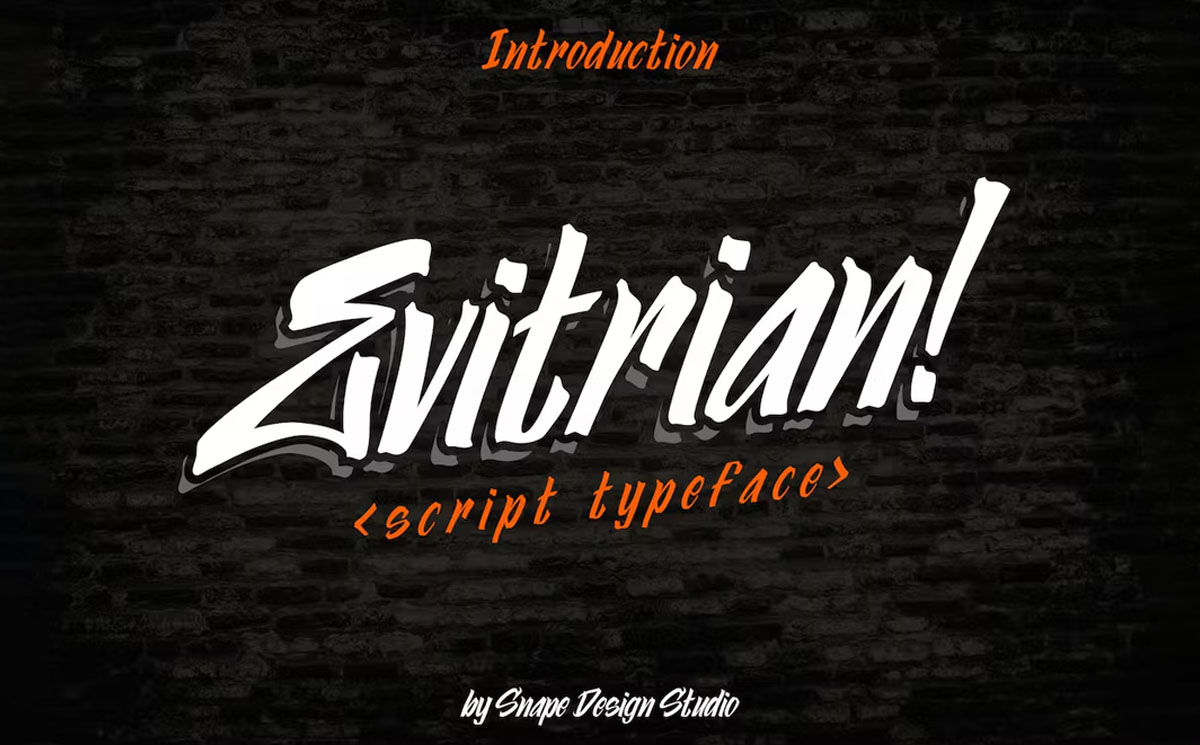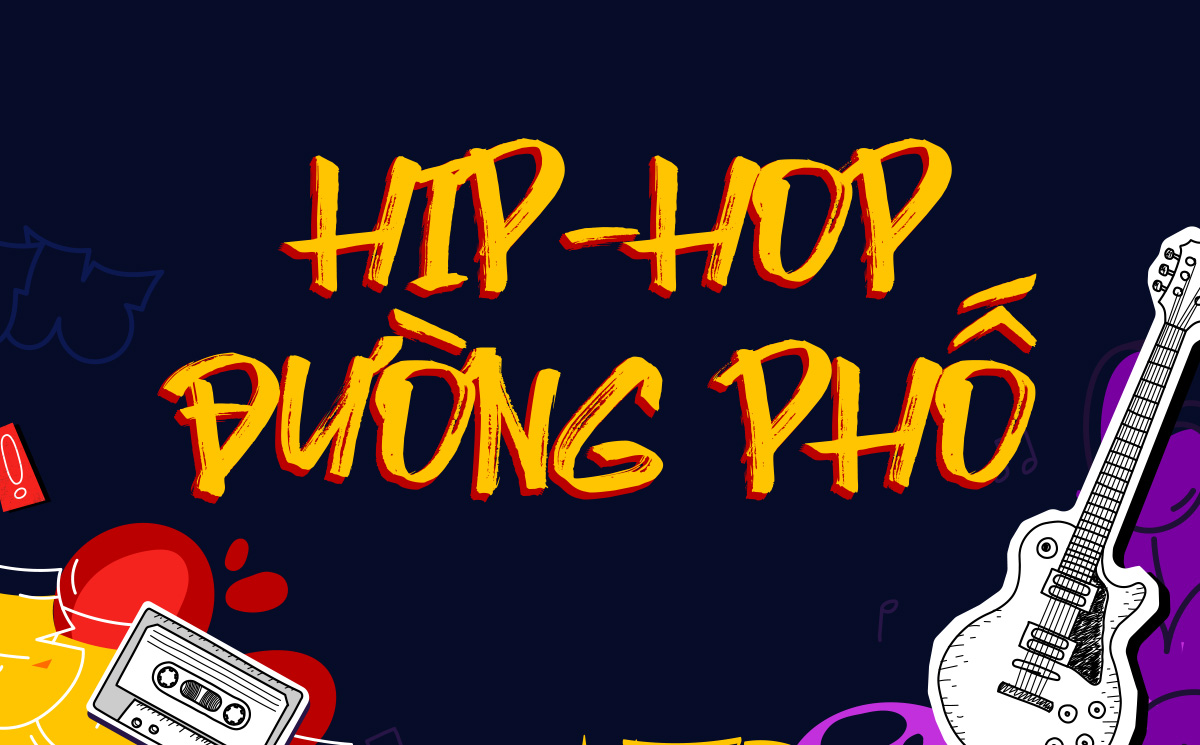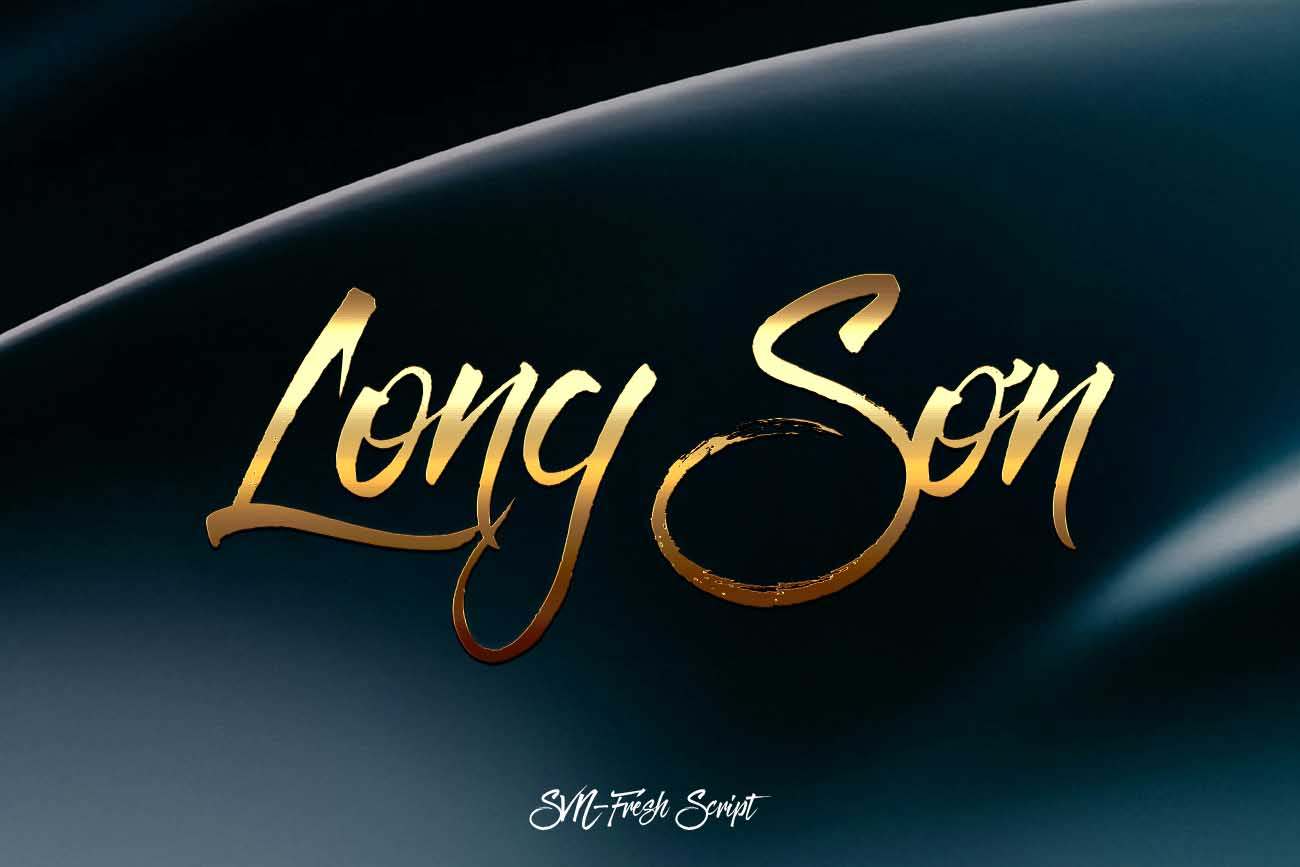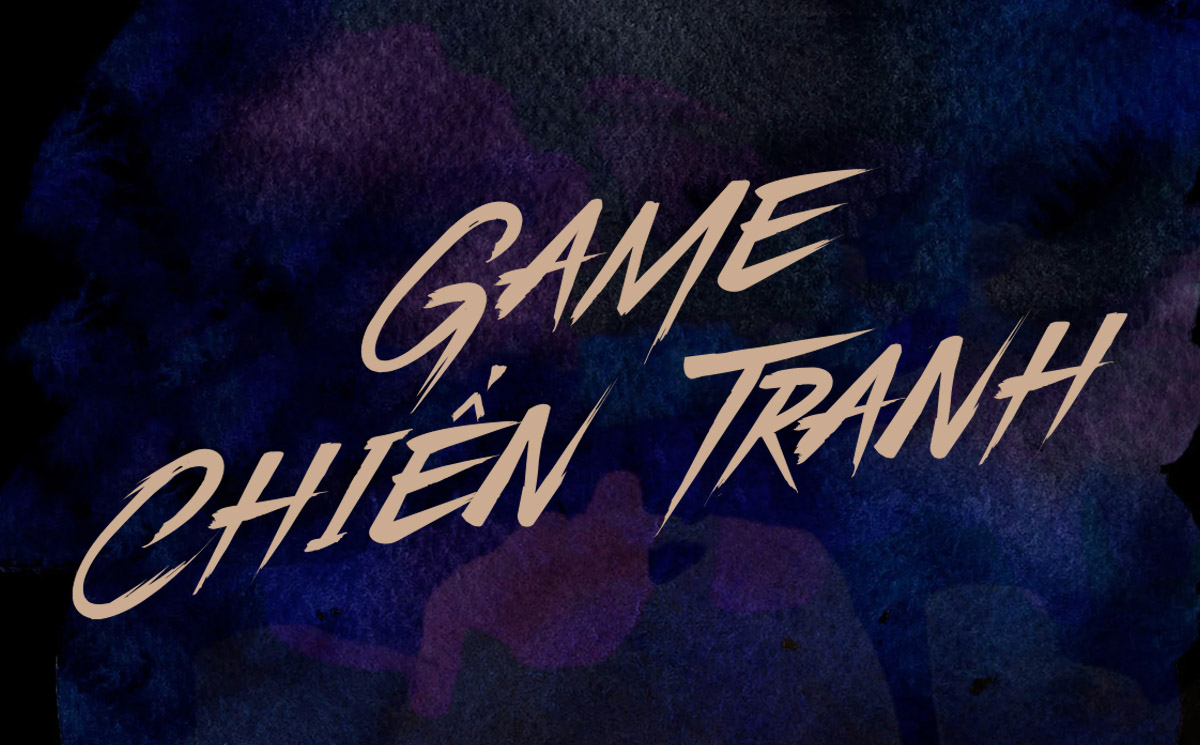
[Tải Xuống] Tổng Hợp Các Font Chữ Graffiti Việt Hóa Đẹp Cho 2026
Khám phá bộ sưu tập font chữ graffiti Việt hóa 2026 đẹp, cá tính, đầy chất đường phố, phù hợp poster, logo, áo thun và thiết kế hiphop.
Trong thiết kế hiện đại, font chữ graffiti đang dần trở thành lựa chọn yêu thích của nhiều nhà thiết kế trẻ bởi sự phóng khoáng, táo bạo và đầy chất nghệ thuật mà nó mang lại. Không chỉ dùng để truyền tải thông điệp, font còn giúp tạo dấu ấn riêng cho thương hiệu hoặc sản phẩm. Nếu bạn đang muốn làm mới thiết kế theo phong cách đường phố năng động, bài viết này chính là nơi để bắt đầu.
Tại Fontdep.vn, chúng tôi đã tuyển chọn những bộ font graffiti Việt hóa đẹp nhất năm 2025 – đa dạng kiểu dáng, dễ sử dụng và đặc biệt là hỗ trợ tiếng Việt đầy đủ. Bạn có thể dùng cho nhiều mục đích như thiết kế áo thun, poster, banner âm nhạc, bìa truyện tranh hoặc logo thương hiệu cá tính.
Font chữ graffiti là gì?
Font chữ graffiti là kiểu chữ lấy cảm hứng từ nghệ thuật vẽ tường đường phố – nơi chữ viết trở thành một phần của biểu đạt cá nhân và phong trào văn hóa. Những font này thường có đường nét to, đậm, được tạo hình một cách tự do, phá vỡ khuôn mẫu truyền thống. Có font nghiêng ngả, có font như chảy sơn hoặc được xịt lên bề mặt tường bằng bình sơn phun.
Phong cách này thường gắn liền với văn hóa hiphop, rap, underground, hoặc những thiết kế mang tinh thần nổi loạn, độc lập và tự do thể hiện bản thân.
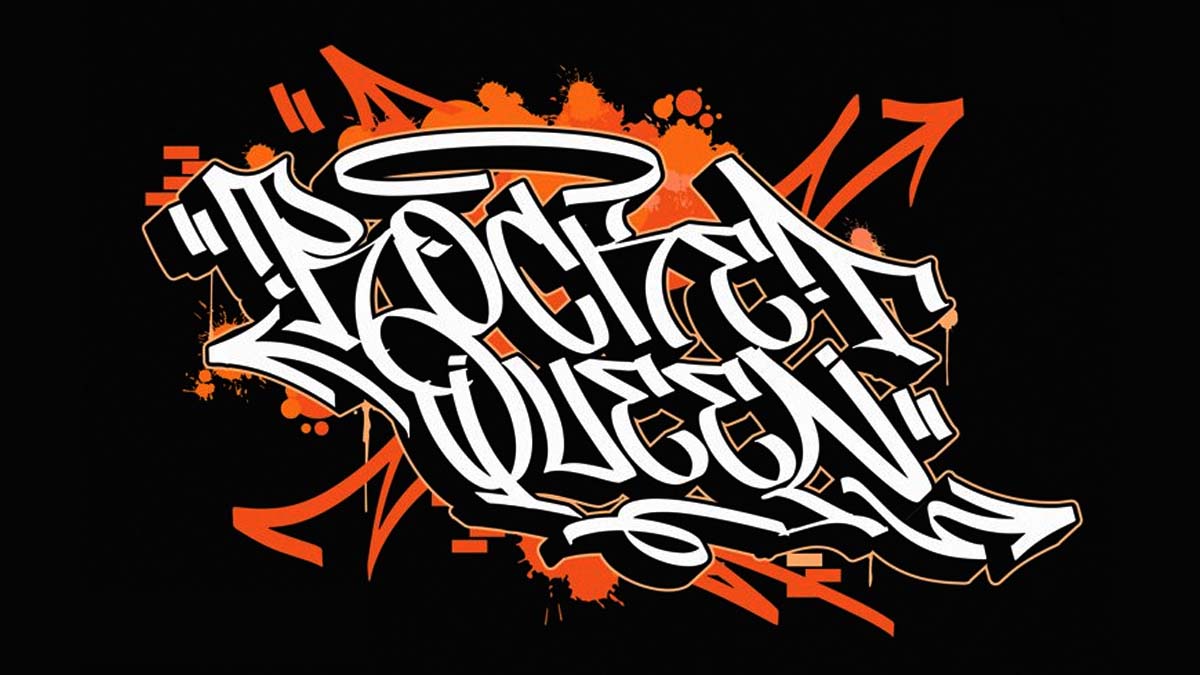
Những điểm nổi bật của font chữ graffiti
- Đường nét mạnh mẽ, không gò bó: Các ký tự được tạo hình đa dạng, không theo một cấu trúc cứng nhắc nào.
- Tính thẩm mỹ đậm chất nghệ thuật: Nét chữ có thể mang phong cách chảy sơn, 3D, bubble hoặc graffiti cổ điển.
- Dễ gây ấn tượng thị giác: Dùng làm tiêu đề, logo hoặc chữ nhấn rất hiệu quả.
- Hỗ trợ tiếng Việt: Nhiều bộ font đã được Việt hóa, có dấu đầy đủ – tiện dụng trong thiết kế nội địa.
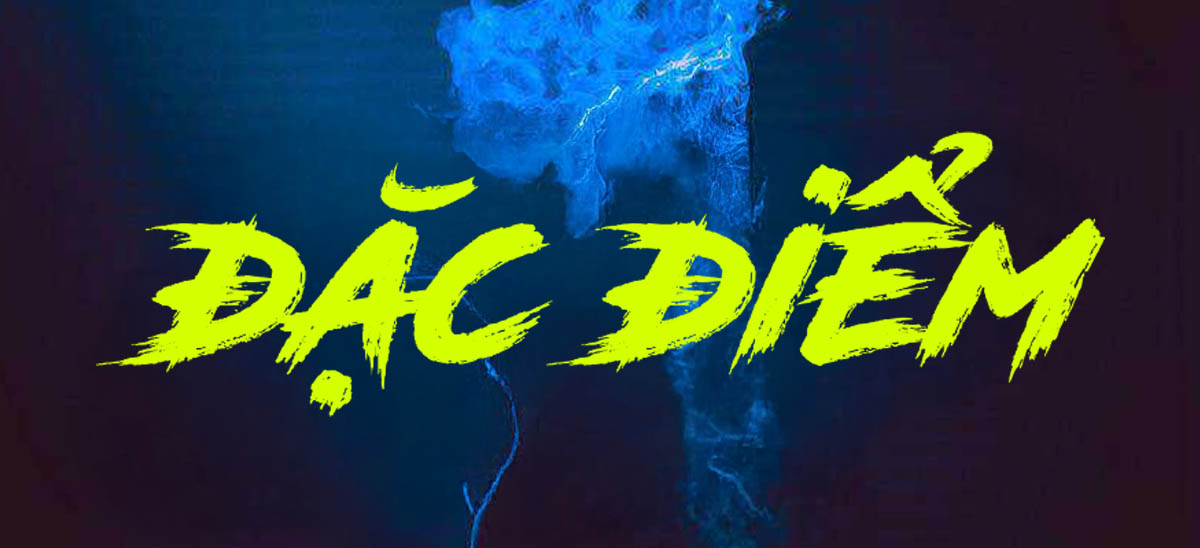
Top 13+ Font chữ graffiti Việt hóa đẹp nhất 2025
Dưới đây là một số font graffiti đã được Việt hóa đầy đủ, dễ sử dụng và cực kỳ ấn tượng trong thiết kế:
1. MJ Brostone – Bay Bổng & Tự Nhiên | Font chữ graffiti Việt hóa
MJ Brostone sở hữu kiểu chữ viết tay bằng cọ với đường nét mềm mại, hơi nghiêng về phải tạo cảm giác uyển chuyển, thoải mái. Các chữ cái có độ cao đồng đều, sắp xếp gọn gàng, giữ được sự ngẫu hứng nhưng vẫn dễ đọc. Phần đuôi chữ được kéo dài tinh tế giúp tổng thể font trở nên sinh động và mang hơi thở hiện đại, phù hợp với nhiều loại thiết kế mang tính cá nhân.
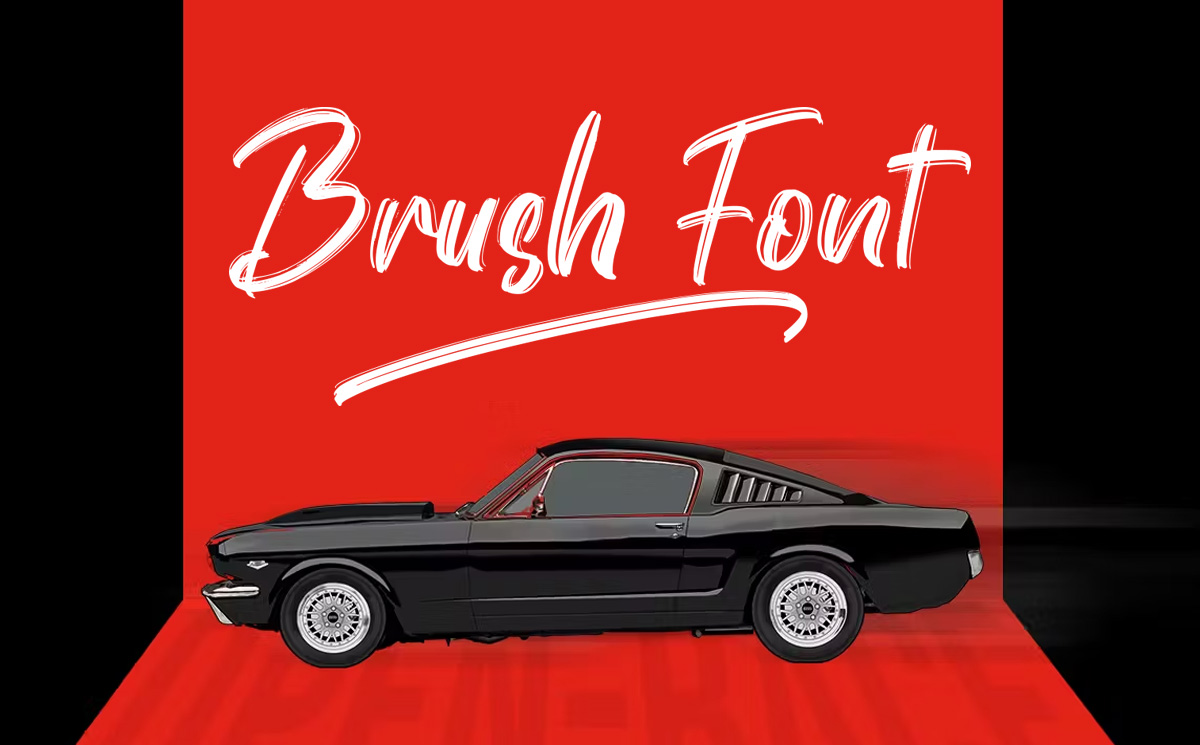
2. SVN Road Rage – Mạnh Mẽ & Bùng Nổ | Font chữ graffiti brush
SVN Road Rage mang đến cảm giác như được vẽ bằng cọ, với những nét chữ lớn, sắc cạnh và có phần rách gân ở đầu hoặc đuôi. Từng ký tự như được hất mạnh tay, tạo nên hiệu ứng chuyển động quyết liệt và đầy tính áp lực. Phông chữ này truyền tải sự khẩn trương, mạnh mẽ và năng lượng bùng nổ – rất thích hợp cho các thiết kế cần gây ấn tượng thị giác mạnh ngay từ cái nhìn đầu tiên.
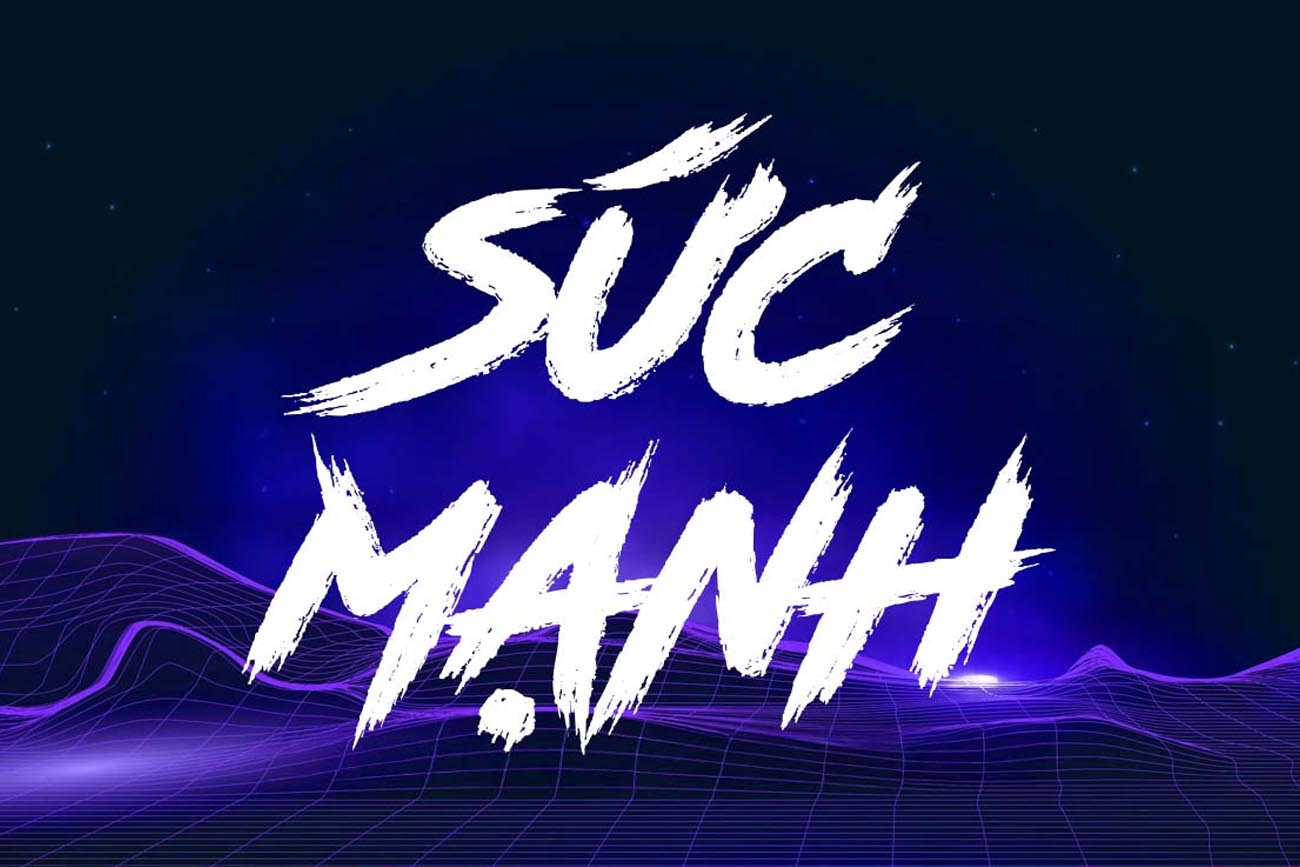
3. SVN Skill – Lả Lướt & Nhịp Nhàng | Font chữ viết tay graffiti Việt hóa
SVN Skill là kiểu chữ viết tay mang phong cách hiện đại với đường nét uyển chuyển và mềm mại. Các ký tự được thiết kế liền mạch, nhiều chữ có đuôi kéo dài tạo nên nhịp điệu thị giác uyển chuyển như một bản nhạc. Font giữ được độ rõ ràng khi đọc nhưng vẫn thể hiện được chất nghệ thuật, thích hợp cho các thiết kế cần chút lãng mạn và chuyển động.
- Tác giả gốc: Misti’s Fonts
- Việt hóa bởi: Team SVN
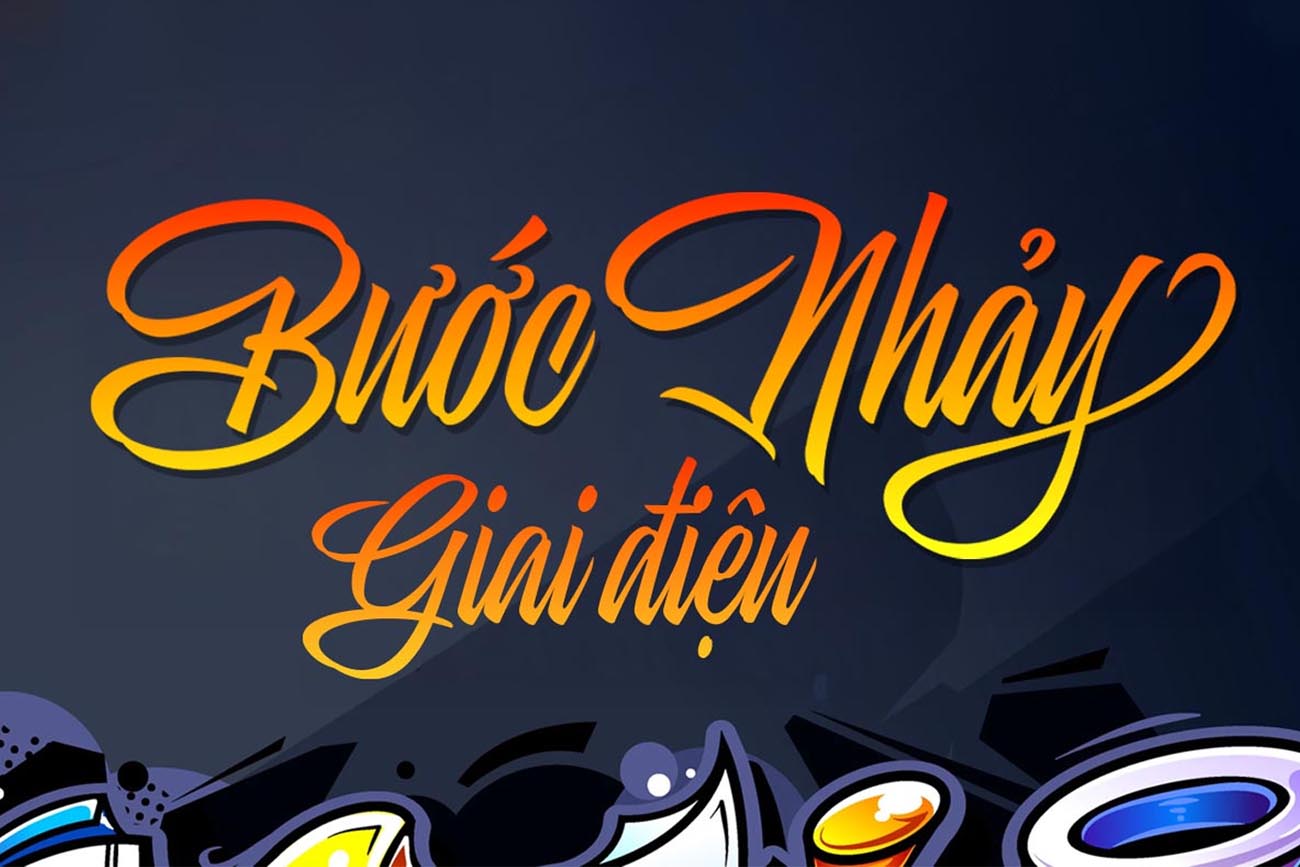
4. SVN Another – Dữ Dội & Kịch Tính | Font chữ graffiti horror Việt hóa
SVN Another mang phong cách chữ cọ đầy táo bạo với nét nhấn nhá đậm chất kinh dị. Các đầu nét nhọn hoắt, phần đuôi chữ như bị xé toạc, tạo nên cảm giác gai góc và bất ổn. Ký tự có độ dày lớn nhưng không đồng đều, góp phần tăng tính kịch tính và căng thẳng thị giác. Đây là lựa chọn lý tưởng cho các thiết kế mang màu sắc giật gân, bí ẩn hoặc theo phong cách horror, phiêu lưu đầy kịch tính.
- Tác giả gốc: Måns Grebäck
- Việt hóa bởi: Team SVN
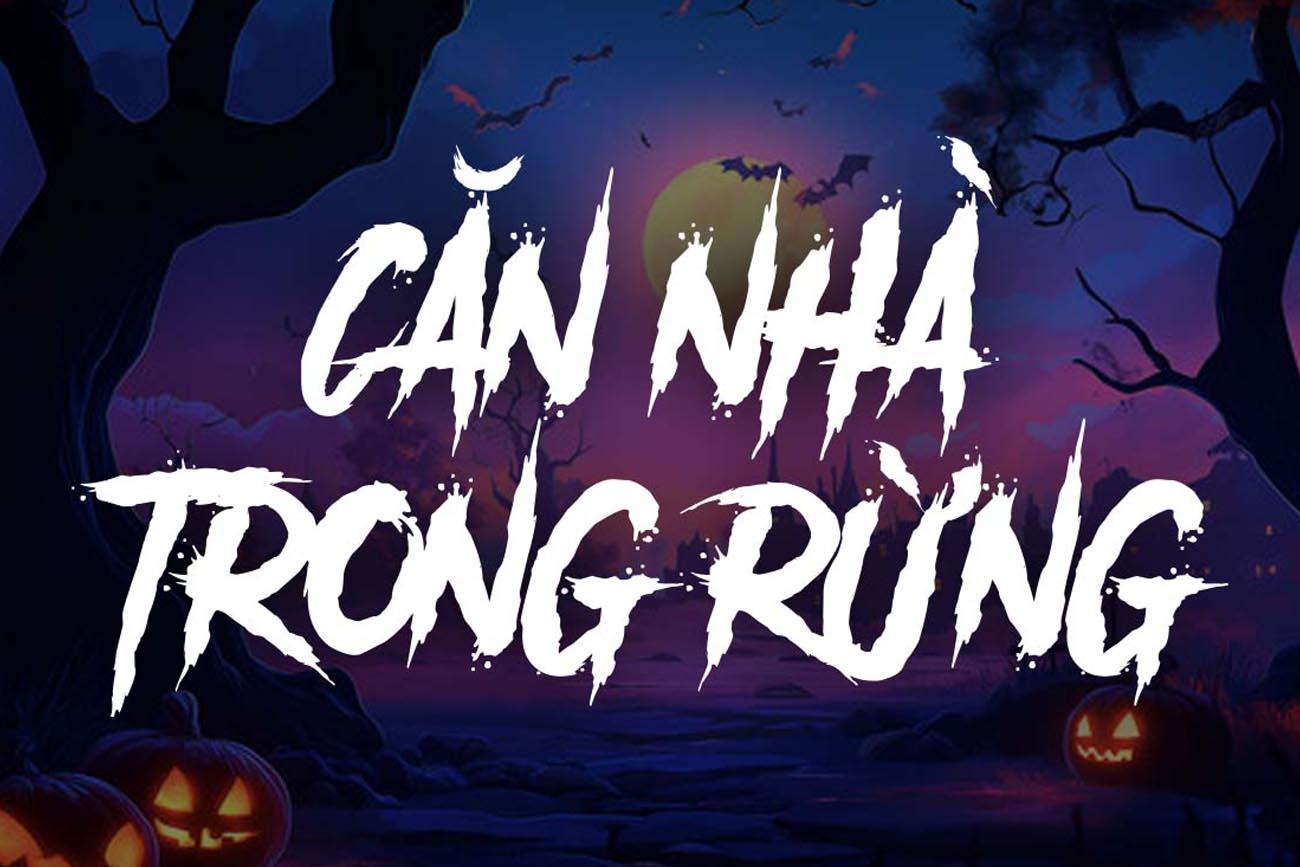
5. SVN Another – Dữ Dội & Kịch Tính | Font chữ graffiti horror Việt hóa
TH Queen Rocker mang phong cách cọ quét mạnh tay, tạo ra các vệt chữ sắc lẹm như được vẽ nhanh bằng bút lông to. Đường nét thô ráp, phần đầu và đuôi chữ thường kéo dài bất quy tắc, tạo cảm giác chuyển động mạnh. Phông chữ này thể hiện năng lượng bùng nổ, phù hợp với thiết kế cần gây ấn tượng ngay từ ánh nhìn đầu tiên.
- Tác giả gốc: 7NTypes
- Việt hóa bởi: Phạm Sơn
6. SVN Evitrian – Cá Tính & Phá Cách | Font chữ hiphop graffiti Việt hóa
SVN Evitrian mang phong cách graffiti script sắc sảo với các nét chữ xiên mạnh, góc cạnh và kéo dài dứt khoát. Ký tự có độ nhấn cao, khoảng cách giữa các chữ được thiết kế chặt chẽ giúp tổng thể trở nên liền mạch. Font gợi cảm giác mạnh mẽ, đường phố nhưng vẫn giữ được độ thanh thoát cần thiết cho các dự án hiện đại và có chủ đích thị giác rõ ràng.
Nếu bạn đang tìm kiếm một cách để tạo điểm nhấn mạnh mẽ và khác biệt cho thiết kế của mình, thì font chữ graffiti Việt hóa chắc chắn là lựa chọn không thể bỏ qua. Với đường nét phóng khoáng, phá cách và đầy cá tính, những bộ font này không chỉ đẹp về hình thức mà còn giúp bạn thể hiện phong cách riêng một cách rõ nét.